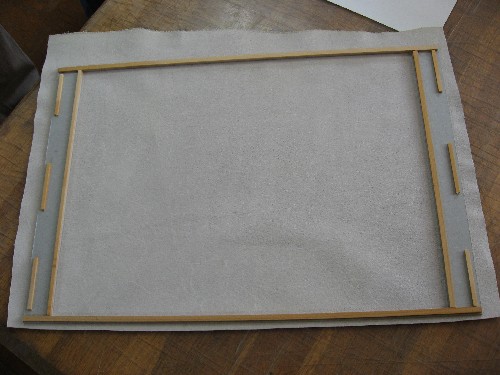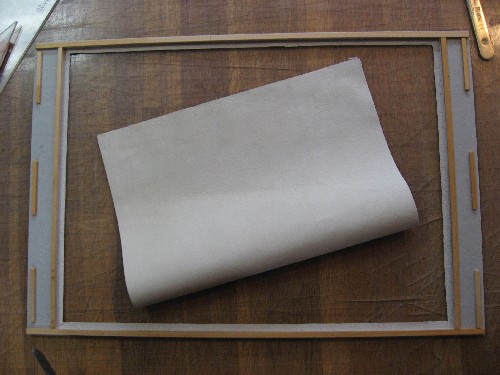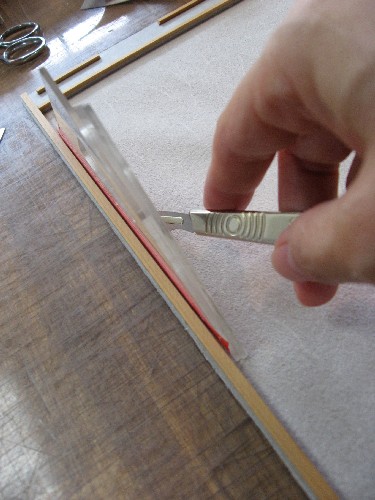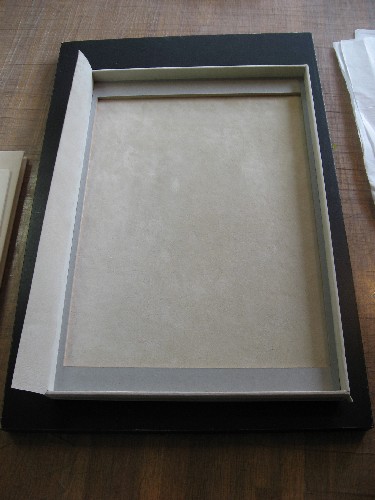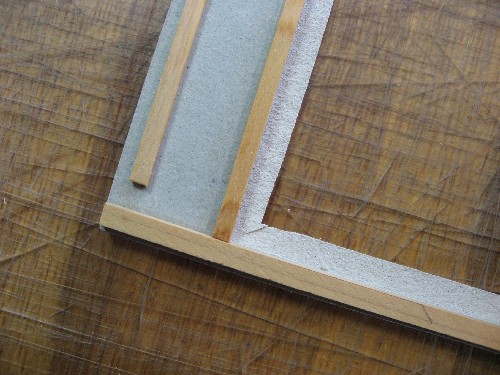
ÌÑÁÛ¤ÎÈ¢£²
ÌÑÁÛ¤ÎÈ¢¤¬¾¯¤·À®Ä¹¤·¤Þ¤·¤¿¡Ä¡£
È¢¤ÎÃæ¤Ë¤ÏËܤξ¤Ë»ñÎÁ¤È¤Ê¤ëºý»Ò¤¬Æþ¤ê¤Þ¤¹¡£¤½¤³¤ÇÃʺ¹¤ò¤Ä¤±¤ëºî¶È¤Ç¤¹¡£¥Á¥Ã¥×¥Ü¡¼¥ë¤ò2Ë玤ë¤È¹â¤¯¤Ê¤ê¤¹¤®¤ë¤Î¤Ç¡¢Î¢Â¦¤Ë2ŽÐŽØ¤ÎËÀ¤òޤêÉÕ¤±¤ÆÄ´À°¤·¤Þ¤·¤¿¡£¤³¤ì¤¾¤Þ¤µ¤·¤¯¡Ö΢¦Á´Éô¸«¤»¤Þ¤¹¡ª¡×¾õÂ֤Ǥ¹¤Í¡Ä¡£É½¤Ë¤Ï¥Ì¥Ð¥Ã¥¯¤òޤêÉÕ¤±¤Þ¤¹¡£
¥Ì¥Ð¥Ã¥¯¤òŽ¤Ã¤¿¸å¡¢¼þ°Ï¤ò¥á¥¹¤ÇºÛ¤ÁÍî¤È¤·¤Þ¤¹¡£²¼¤Ë¤Ï°ìÌ̤˥«¥Ã¥Æ¥£¥ó¥°¥Þ¥Ã¥È¤¬Éߤ¤¤Æ¤¢¤ê¤Þ¤¹¤¬¡¢¤³¤Î¥Þ¥Ã¥È¤Ë¥á¥¹¤Î¿Ï¤¬Æþ¤ê¹þ¤à¤¯¤é¤¤¤Î´¶³Ð¤ÇÀڤäƤ¤¤¯¤È¡¢¥Ì¥Ð¥Ã¥¯¤¬°ú¤Ã¤Ñ¤é¤ì¤ë¤³¤È¤â¤Ê¤¯¾å¼ê¤¯ÀÚ¤ì¤Þ¤¹¡£
ÎϤòÆþ¤ì¤º¤Ë°ú¤Ã¤Ñ¤Ã¤Æ¤¤¤¯¤À¤±¤À¤È¡¢¥Ì¥Ð¥Ã¥¯¤ÏÇö¤¯½À¤é¤«¤¤¤Î¤Ç¡¢°ú¤¤º¤Ã¤Æ¤¦¤Þ¤¯ÀÚ¤ì¤Ê¤¤¤Î¤Ç¤¹¡£¥Þ¥Æ¥ê¥¢¥ë¤Ë¤è¤Ã¤ÆÎÏ¤ÎÆþ¤ì¶ñ¹ç¤âÊѤï¤ê¤Þ¤¹¤Í¡Ä¡£
¤µ¤Æ¤³¤³¤Ç¡¢Î¢µ»¤ò¤Á¤ç¤Ã¤È¡Ä¡£
ÏÈ¤ÎÆâ¦¤Î¥Ì¥Ð¥Ã¥¯¤âÀÚÈ´¤«¤Ê¤±¤ì¤Ð¤Ê¤é¤Ê¤¤¤Î¤Ç¤¹¤¬¡¢¼þ°Ï¤Î¹â¤µ¤Ë¹ç¤ï¤»¤Æ4¥ß¥ê¤ÎÉý¤ò¤È¤Ã¤ÆÀÚÈ´¤¯¤³¤È¤Ë¤Ê¤ê¤Þ¤·¤¿¡£¤³¤¦¤¤¤¦»þ¤Ë¤ÏÄ구¤Ç¬¤Ã¤ÆÀþ¤ò°ú¤¤¤Æ¡Ä¤È¤¤¤¦ºî¶È¤â¤¢¤ê¡ª¤Ç¤¹¤¬¡¢¤â¤¦¾¯¤·´Êñ¤ÊÊýË¡¤ò¶µ¤ï¤ê¤Þ¤·¤¿¡£¾®¤µ¤Ê»°³ÑÄ구¤ò2Ëç¹ç¤ï¤»¤ë¤È4¥ß¥ê¼å¤ÎÉý¤¬ÆÀ¤é¤ì¤Þ¤¹¡£4¥ß¥ê¤Ë¶á¤Å¤±¤ë¤Ë¤Ï¤É¤¦¤·¤¿¤é¡Ä¡©¤½¤³¤Ç³èÌö¤¹¤ë¤Î¤¬¥Þ¥¹¥¥ó¥°¥Æ¡¼¥×¤Ç¤¹¡£¿ôË玤äÆÈù̯¤Ê¸ü¤µ¤òÄ´À°¤·¤Þ¤¹¡£¤³¤ì¤ÏÊØÍø¡ªÌܤ«¤é¤Þ¤¿¤Þ¤¿ÎÚ¤¬Íî¤Á¤Þ¤·¤¿¡£¡Ê»äÎÚ»ý¤Á¡Ä¡©¡Ë
¤³¤¦¤·¤ÆÄ´À°¤·¤¿»°³ÑÄ구¤ò¼þ°Ï¤ÎÏȤˤ¢¤Æ¤Æ¡¢Æâ¦¤òÀڤäƤ¤¤±¤Ð¡¢Èæ³ÓŪ´Êñ¤Ë¤º¤ì¤ë¤³¤È¤â¤Ê¤¯ºî¶È¤¬¤Ç¤¤Þ¤¹¤Í¤§¡Á¡£
¤µ¤Æ¤µ¤Æ¡¢Æâ¦¤òÀÚÈ´¤¤¤Æ´°Î»¤Ç¤¹¡£
¥á¥¹¤Î¿Ï¤âÀÚ¤ê¤Ë¤¯¤¯¤Ê¤Ã¤¿¤éÊѤ¨¤Þ¤·¤ç¤¦¡£
Àڤ俥̥Х寤òÆâ¦¤ËÅݤ·¤ÆÅ½¤ë¤Î¤Ç¤¹¤¬¡¢³Ñ¤ËÀÚ¹þ¤ß¤òÆþ¤ì¤Ê¤±¤ì¤Ð¤Ê¤ê¤Þ¤»¤ó¡£
¤³¤ÎºÝ¡¢³Ñ¤ÎÆâ¦¤¤¤Ã¤Ñ¤¤¤ËÀÚ¹þ¤à¤È¤¤ì¤¤¤Ëޤì¤Ê¤¤¤Î¤Ç¡¢Æâ¦¤«¤é1¥ß¥ê¤°¤é¤¤¤ò»Ä¤·¤ÆÀÚ¹þ¤à¤È¤è¤¤¤è¤¦¤Ç¤¹¡£
ºî¶ÈÃæ¤Ë¡¢ËܤËȯÀ¸¤¹¤ë¤·¤ß¤Î¤è¤¦¤Ê¸½¾Ý¤ÎÏä·¤¬½Ð¤Þ¤·¤¿¡£
Ëܤλæ¤ËÃã¿§¤ÎÊÑ¿§¤¬¸«¤é¤ì¤Þ¤¹¤Í¡Ä¡£¤³¤ì¤Ï¡Öfoxing¡Ê¥Õ¥©¥¯¥·¥ó¥°¡Ë¡×¤È¸Æ¤Ö¤½¤¦¤Ç¤¹¡£²¿¤Ç¡Ö¤¤Ä¤Í¡¦fox¡×¤Ë¡Öing¡×¤Ê¤Î¤Ç¤·¤ç¤¦¡Ä¡£¸ì¸»¤¬ÃΤꤿ¤¤¤Ç¤¹¡£
¹õ¤Î³Ú¤·¤ß
°ÊÁ°¤â¤´¾Ò²ð¤·¤¿¤Î¤Ç¤¹¤¬¡¢·î¤Ë£²²ó¤Î¥É¥í¡¼¥¤¥ó¥°¤Ï¤¤¤Ä¤â³Ú¤·¤¤»ö¤ò¤µ¤»¤Æ¤â¤é¤¨¤ë¼Â¤Ë³Ú¤·¤¤¥¯¥é¥¹¤Ê¤Î¤Ç¤¹¡¢¡ÊÀèÀ¸¤¢¤ê¤¬¤È¤¦¡ª¡Ë¡¡
¤½¤·¤Æº£²ó¤Ï¥³¥é¡¼¥¸¥å¤ËÄ©Àï¤Ç¤¹¡£¤Þ¤º¥³¥é¡¼¥¸¥å¤Ë»È¤¦»æ¤òºî¤ê¤Þ¤¹¡£¿§ÉÕ¤¤â¤¿¤¯¤µ¤óºî¤Ã¤¿¤Î¤Ç¤¹¤¬¡¢º£Æü¤Ï¹õ¤À¤±¤ÎÊý¤ò¤´¾Ò²ð¡£
¹õ¤Î¥¢¥¯¥ê¥ë³¨¶ñ¤À¤±¤ÇÌÏÍͤòÉÕ¤±¤Þ¤·¤¿¡£¥Ù¥¿¤âºî¤Ã¤¿¤ê¤¤¤í¤¤¤í¤Ê¥Æ¥¯¥¹¥Á¥ã¡¼¤ò¼Â¸³¤Ç¤¹¡£
»²²Ã¼Ô¤½¤ì¤¾¤ì¤¬°ìÀ¸·üÌ¿½¸Ã椷¤Æ¤ä¤ê¤Þ¤¹¤¬¡¢»þ¡¹²æ¤ËÊ֤äƥեÈÎÙ¤ò¸«¤ë¤È¡¢¥¢¥é¡ªÂ¾¤Î¿Í¤Î¤ä¤Ã¤Æ¤¤¤ë»ö¤¬µ¤¤Ë¤Ê¤ë¡ª¡¡¤½¤¦¤Ê¤Î¤Ç¤¹¡¢¤³¤¦¤¤¤¦ºî¶È¤Ï°ì¿Í¤Ç¤Ï¤Ä¤Þ¤é¤Ê¤¤¡£²¿¿Í¤«¤Ç¤ä¤ë¤È³Ú¤·¤¤¤Î¤Ç¤¹¡Á¡Á¡¡¤É¤¦¤ä¤Ã¤¿¤Î¡©¤ï¤¿¤·¤â¤ä¤í¤¦¤Ã¤È¸À¤¦´¶¤¸¡£
¡Êmojitor-h¤µ¤ó¤Îºî¤Ã¤¿Ãæ¤Ë¥¯¥âȯ¸«¡Ë
¼¡²ó¤³¤Î»æ¤ÏÀÚ¤ê¹ï¤Þ¤ì¤Æ¡¢¤ª¤â¤·¤í¤¤¥³¥é¡¼¥¸¥å¤Ø¤ÈÊѿȤÎͽÄê¡£¡Ê¤¢¤¯¤Þ¤Ç¤â¡¦¡¦¡¦Í½Äꡦ¡¦¡¦¡Ë
¤É¤ó¤Ê¤³¤È¤Ë¤Ê¤Ã¤Æ¤¤¤¯¤Î¤«¡¢¤Þ¤¿¼¡²ó¤Î¤ª³Ú¤·¤ß¤Ç¤¹¡£
¥¤¥á¡¼¥¸¤È¤·¤Æ¤Ï¥ß¥í¤Î¤è¤¦¤Ê´¶¤¸¤Ë¤·¤¿¤¤¡ª¤Ç¤â̵Íý¤«¡¼¡ª
¤½¤ì¤Ë¤·¤Æ¤â¡¢¹õ¤À¤±¤Ç¤³¤ó¤Ê¤Ë³Ú¤·¤¤¤Ê¤ó¤Æ¤Í¡Á¡£¤º¡¼¤Ã¤È¤ä¤Ã¤Æ¤¤¤¿¤¤¤¯¤é¤¤¤Ç¤·¤¿¡£
¤â¤Á¤í¤óºÇ½ªÅª¤Ë¤Ïʸ»ú¤òÆþ¤ì¤Æ¤¤¤¤Þ¤¹¡£¥«¥ê¥°¥é¥Õ¥£¡¼ºîÉʤȤ·¤Æ´°À®¤¹¤ë¤«¤É¤¦¤«¡ª
¥·¥ç¡¼¥ó¡¦¥é¥ó¥À¡¼¥¹Å¸
½©¤Ï¡¢¥¢¡¼¥È¤Îµ¨Àá¡£Èþ½Ñ´Û¤â³¨²èŸÌÜÇò²¡¤·¡£¤Ç¤â¡¢¤æ¤Ã¤¯¤ê¥¢¡¼¥È¤Ë¤Ò¤¿¤ê¤¿¤¤¤Ê¤é¤Ð¡¢¥®¥ã¥é¥ê¡¼¤¬¤ª´«¤á¡£ÌµÎÁ¤À¤·¡¢¿Íº®¤ß¤Ï¤Ê¤¤¤·¡¢¤¤¤¤¶õ´Ö¤òÆÈ¤êÀê¤á¤Ê¤ó¤Æ¾ì¹ç¤â¡©¡ª¤È¤¤¤Ã¤Æ¤â¾ì°ã¤¤¤Êµ¤¸å¤ì¤¹¤ë¤è¤¦¤ÊÊ·°Ïµ¤¤Î¾ì¹ç¤â¤¢¤ë¤«¤â¤Ç¤·¤Æ¡¢¤Þ¤¢¡¢¤½¤³¤Ï¡¢¸«¤ë¤ó¤À¤È¤¤¤¦µ¤¹ç¤Ç¥«¥Ð¡¼¤Ç¤¹¡£
¤µ¤Æ¡¢Ä«Æü¿·Ê¹¤ËÆþ¤Ã¤Æ¤¤¿¥¨¥ë¡¦¥¢¡¦¥È¡¼¥¥ç¡¼¤Î£Ö£ï£ì¡¥£¶¤ÎÆÃ½¸¤Ï¡¢Enjoy ART¡£Ëè²ó¡¢Åìµþ¤¬¼«Ê¬¤Î¸½¼Â¤«¤é¤Ï¡¢¤«¤±¤Ï¤Ê¤ì¤¿ÅԻԤʤó¤À¤Ê¤¢¤È´¶¤¸¤ëµ»ö¤Ð¤«¤ê¤Ç¤¹¤¬¡¢º£²ó¥â¥À¥ó¥¢¡¼¥È¤Î¥®¥ã¥é¥ê¡¼¤Î¾Ò²ð¥Ú¡¼¥¸¤¬¤¢¤ê¡¢¾ì½ê¤Ï¤É¤³¡©¤È¤ß¤ì¤Ð¡¢¤³¤Î¤Þ¤¨¡¢Ì¤äƤ¿¤É¤êÃ夯¤Î¤Ë»þ´Ö¤¬¤«¤«¤Ã¤Æ¤·¤Þ¤Ã¤¿¡¢Æ±¤¸À¶À¡¤ÎÁҸˤÎÃæ¤Ë¤¢¤ë¥®¥ã¥é¥ê¡¼¡£¥â¥À¥ó¥¢¡¼¥È¤Î¥®¥ã¥é¥ê¡¼¤¬½¸¹ç¤·¤Æ¤¤¤ë¤È¤³¤í¤À¤Ã¤¿¤Î¤À¤È¡¢¤½¤ì¤Ç¡¢¤Ï¤¸¤á¤Æ¤ï¤«¤Ã¤¿¤ï¤±¤Ç¤¹¡£¤¹¤Ã¤¤ê¡ª
¤½¤·¤Æ¡¢»ä¤¬¡¢¤Û¤ó¤È¤Ë¤³¤ó¤Ê¤È¤³¤í¤Ë¥®¥ã¥é¥ê¡¼¤¬¡©¤Èõ¤·¤Æ¸«¤Ë¹Ô¤Ã¤¿¤Î¤Ï¡¢¥·¥ç¡¼¥ó¡¦¥é¥ó¥À¡¼¥¹¤È¤¤¤¦¥Ë¥å¡¼¥è¡¼¥¯¤Îºî²È¤ÎºîÉʤΟ¼¨¡£Èà¤ÎºîÉʤΥ·¥ê¡¼¥º¤ÎÃæ¤Î¥Æ¥¥¹¥È¼çÂΤȤ·¤¿¥Ú¥¤¥ó¥Æ¥£¥ó¥°¤Ë¶½Ì£¤ò»ý¤Á¤Þ¤·¤¿¡£
ÁҸˤι⤤ŷ¾å¡¢¹¡¼¤¤¶õ´Ö¤Ë»ä¤Ò¤È¤ê¡£¸ÀÍÕ¤¬´ö½Å¤Ë¤â½Å¤Ê¤ê¹ç¤Ã¤¿Â礤ʺîÉʤˤ«¤³¤Þ¤ì¡¢¤È¤Æ¤â¾®¤µ¤Ê¸ºß¤Î»ä¡£¤½¤ÎÃæ¤ÇÌܤòα¤á¤¿¤Î¤Ï¡¢»ä¤¬ÃΤäƤ¤¤½¤¦¤Êñ¸ì¤¬ÆÉ¤ß¼è¤ì¤ëºîÉÊ¡£¤ï¤«¤é¤Ê¤¤¤Î¤Ï¡¢ÅŻҼ½ñ¤Ë¤¿¤è¤Ã¤Æ¤Ã¤È....
depression,betray,greed,rage,lust,revenge,coward,frustration,guilt,health,pride,sickness,
anger,sorrow,drunk,madness,envy,fatigue,remorse,sloth,regret,paranoid,fear,burst
¤½¤ì¤é¤Ï¡¢¤É¤Á¤é¤«¤È¤¤¤¦¤ÈÉé¤Î¸ÀÍդǤ¹¤¬¡¢ÌÀ¤ë¤¤Â¿¿§¤Î¥Ú¥¤¥ó¥È¤Ç½ñ¤«¤ì¤Æ¤¤¤Æ¡¢¸«¤¿Ìܤ¬³Ú¤·¤²¤À¤«¤é¤«¡¢¤Ê¤ó¤«¿¼¡¼¤¤¡£¤½¤Î²£¤ÎºîÉʤϡ¢È¿ÂФËhappy,bliss,euphoria....¡¡¤½¤ÎÂоݤ¬¤ª¤â¤·¤í¤¤¡£Ê¸»ú¤È¤¤¤¦¤³¤È¤Ç¡¢¤Á¤ç¤Ã¤È¿È¶á¤Ë´¶¤¸¤¿¥â¥À¥ó¥¢¡¼¥È¡£¿¿¤óÃæ¤Ë°Ø»Ò¤Ç¤â¤¢¤Ã¤¿¤é¡¢¤º¤Ã¤ÈºÂ¤Ã¤Æ¥Ü¡¼¤Ã¤È¤Ê¤¬¤á¤Æ¤¤¤¿¤«¤Ã¤¿.....
¤½¤Î¥®¥ã¥é¥ê¡¼¤ËÃÖ¤¤¤Æ¤¢¤Ã¤¿¡¢Contemporary Art Exibitions in Tokyo NEW favorite¤È¤¤¤¦°ìÍ÷¤ò¤ß¤ë¤È¡¢À¶À¡Çò²Ï°Ê³°¤Ë¤â¡¢¥®¥ã¥é¥ê¡¼¤¬¿À³Úºä¡¢Ï»ËÜÌڤ˸ǤޤäƤ¢¤ë¤è¤¦¤Ç¤¹¡£Å·µ¤¤Î¤è¤¤Æü¡¢¶õ¤¤¤¿»þ´Ö¤Ë¥®¥ã¥é¥ê¡¼¤á¤°¤ê¤¤¤¤¤«¤â¡£À¶À¡Çò²Ï¡¢º£ÅٹԤ俤顢À¶À¡Äí±à¤âΩ¤Á´ó¤ê¤¿¤¤¤È¤³¤í¤Ç¤¹¡£
¹¬¤»¤ò¤¯¤ì¤ë¿Í
ÀèÆü¤Î¥Ö¥í¥°mojitor-h¤µ¤ó¤Î¥Õ¥§¥ë¥È¤Î¥Î¡¼¥È¡¢¤Õ¤«¤Õ¤«¤Õ¤ï¤Õ¤ï¤Î¼ê¤¶¤ï¤ê¤¬ÅÁ¤ï¤Ã¤Æ¤¯¤ë¤è¤¦¤Ç¤·¤¿¤Í¡£
¡Ökritzeln¡×¤è¤¦¤¹¤ë¤Ë¤Ê¤°¤ê½ñ¤¤Ë¶á¤¤¾õ¶·¤Ç¤¹¡£¤¤¤äÍî½ñ¤¤½¤Î¤â¤Î¤Ç¤·¤ç¤¦¤«¡Ä¡£
¤¯¤·¤ã¤¯¤·¤ã´¶¤ò½ñ¤¤¤Æ¡¢½ñ¤¤¤Æ¤¤¤¤Þ¤¹¡Ä¡£
°ìÈÖ³Ú¤·¤¤»þ´Ö¤Ç¤¹¡£
¥¥ã¥Ù¥ÄÀþ¤Ï½ê¤òÊѤ¨¡¢Éۤξå¤Ë¤âÉñ¤¤¹ß¤ê¤Þ¤·¤¿¡£
¥×¥ê¥ó¥È¤´¤Ã¤³¤Î¤ªÀ¤ÏäˤʤꡢËãÉۤξå¤Ç¥°¥ê¥°¥ê¡¢
¥¯¥·¥ã¥¯¥·¥ã¡¢¥Ó¥í¥Ó¥í¤·¤Æ¤¤¤Þ¤¹¡Ä¡£
¤¢¡Á¡¢¥¥ã¥Ù¥ÄÀþ¤Ë¤Ïscissor sisiters ¡ÖI don't feel like dancin'¡×
¤ÎÄ´»Ò¤Î´¶¤¸¤¬»÷¹ç¤¤¤Þ¤¹¡£¡Ê¸Ä¿ÍŪ°Õ¸«¤Ç¤¹¤¬¡Ë
¼¡²ó¤Ï¶ÌǬÀþ¤Ç¤¹¡£¤¢¤Ê¤¿¤Ï¤É¤ó¤ÊÌîºÚÀþ¤ò½ñ¤¤Þ¤¹¤«¡©
¡Ö¤¨¤Ã¡©¤½¤ó¤Ê¥Ð¥«¤Ê¥Þ¥Í¤Ï¤·¤Ê¤¤¡©¡×¢ª¡Ö¤´ÌÀ²ò¤«¤â¡Ä¡×